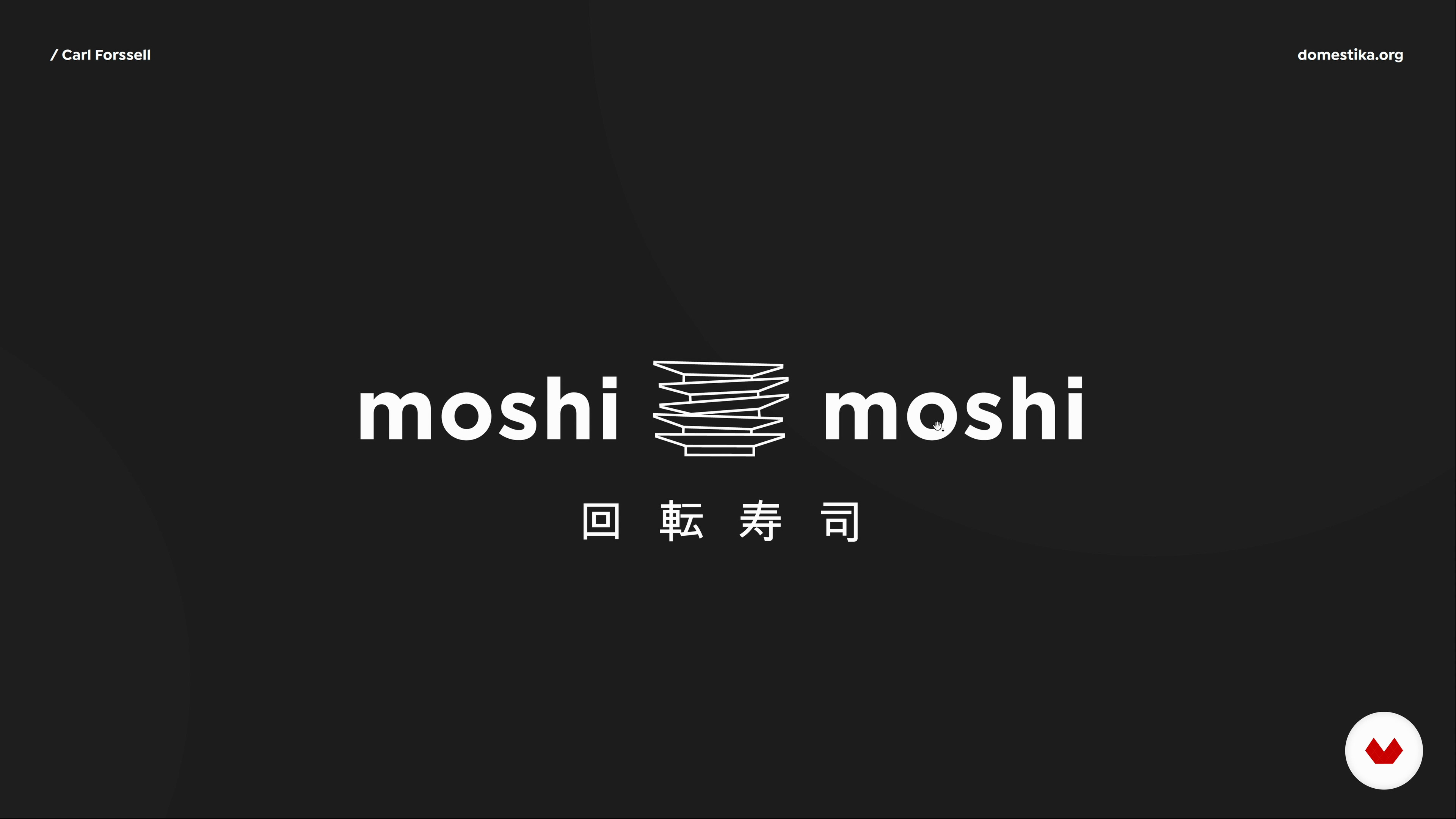
Typografie zur Formel
Über die Videolektion: Typografie zur Formel
“Was wäre unser Symbol ohne die Begleitung seiner Typografie? Dies trägt dazu bei, unsere Botschaft zu verstärken. Ich werde Ihnen zeigen, welche Schritte ich befolgen muss, um die beste typografische Wahl zu treffen.”
In dieser Videolektion behandelt Carl Forssell das Thema: Typografie zur Formel, das Teil dieses Domestika-Onlinekurses ist: Minimalistisches Branding: Klare und direkte Bilder erstellen. Lerne, wie du die visuelle Identität einer Marke in einem minimalistischen Stil entwickelst, vom ersten Konzept bis zur Kundenpräsentation.
Partielle Transkription des Videos
“Typografie zur Formel Was wäre das Symbol ohne die Gesellschaft der Typografie? um Ihre Botschaft zu verstärken? Jetzt zeige ich Ihnen, welche Schritte zu befolgen sind um die beste Schriftart zu finden. Kommen Sie mit mir, um es zu sehen. Typografie zur Formel Es gibt einen Satz von Erik Spiekermann, den ich sehr mag: „Schriften sind magisch. Sie vermitteln nicht nur Informationen über ein Wort, Sie vermitteln eine unterschwellige Botschaft. Für mich spielen Schriftarten eine sehr wichtige Rolle. in unserer Identität. Wir müssen wissen, dass Schriften uns auch eine Geschichte vermitteln, u...”